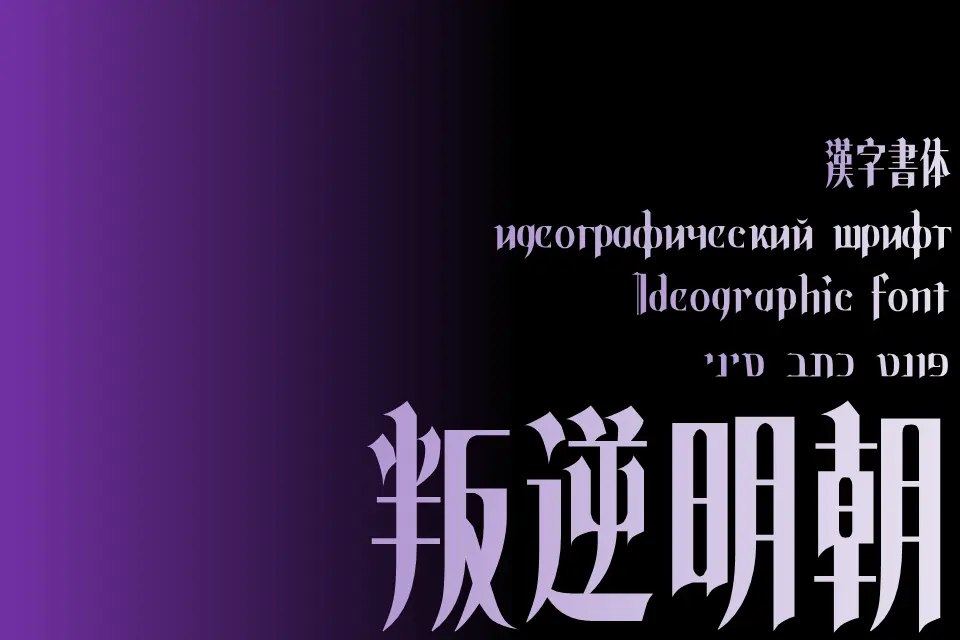
叛逆明朝(Hangyaku Font)是一款開源免費字體,由日本設計師daredemotypo創作,設計風格大膽獨特。Hangyaku這個詞在日語中的意思是“反叛”,因此這個字體的名稱也代表了設計師的反傳統和創新的態度。
叛逆明朝採用了哥特式的設計風格,同時又融合了一些傳統字體的元素,使其看起來更加獨特。其字形輪廓非常簡潔,線條流暢而有力,讓整個字體看起來非常清晰易讀。設計感強烈,它能夠幫助設計師在印刷品、網頁設計和廣告設計等方面展現出獨特的風格和個性。
這款字體適用於繁體,目前簡體中文缺字數嚴重,不建議簡體中文用戶使用。